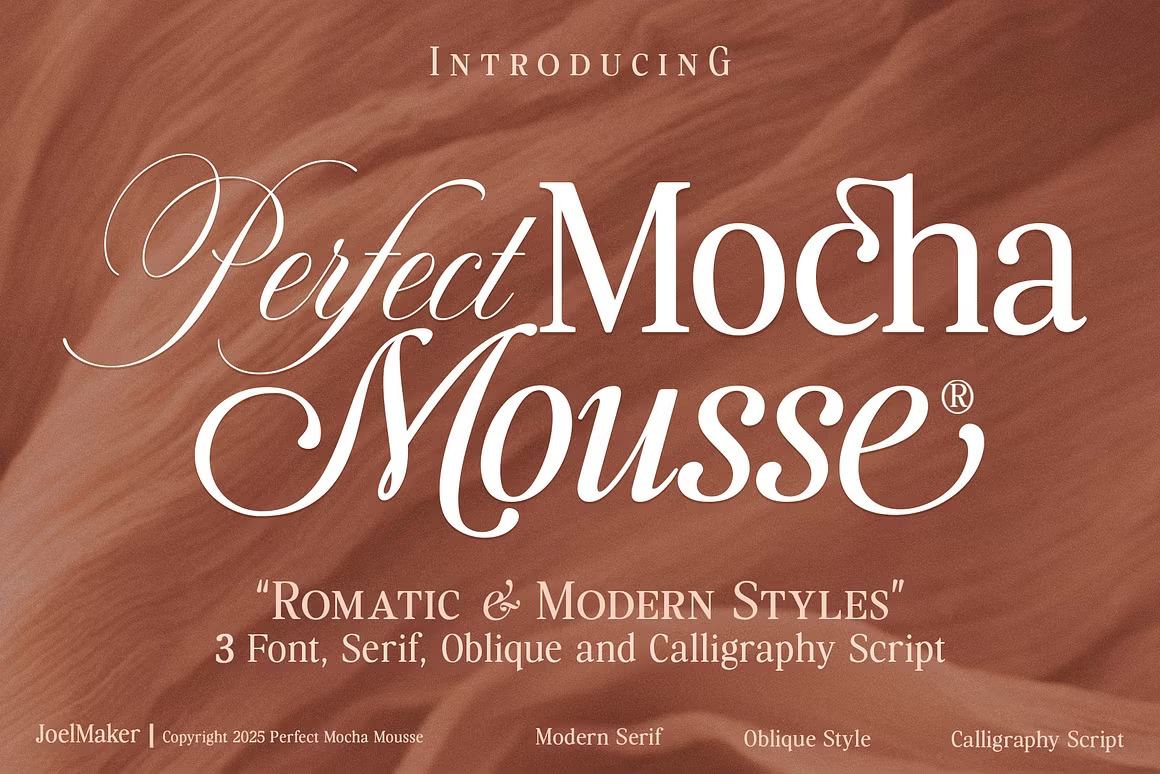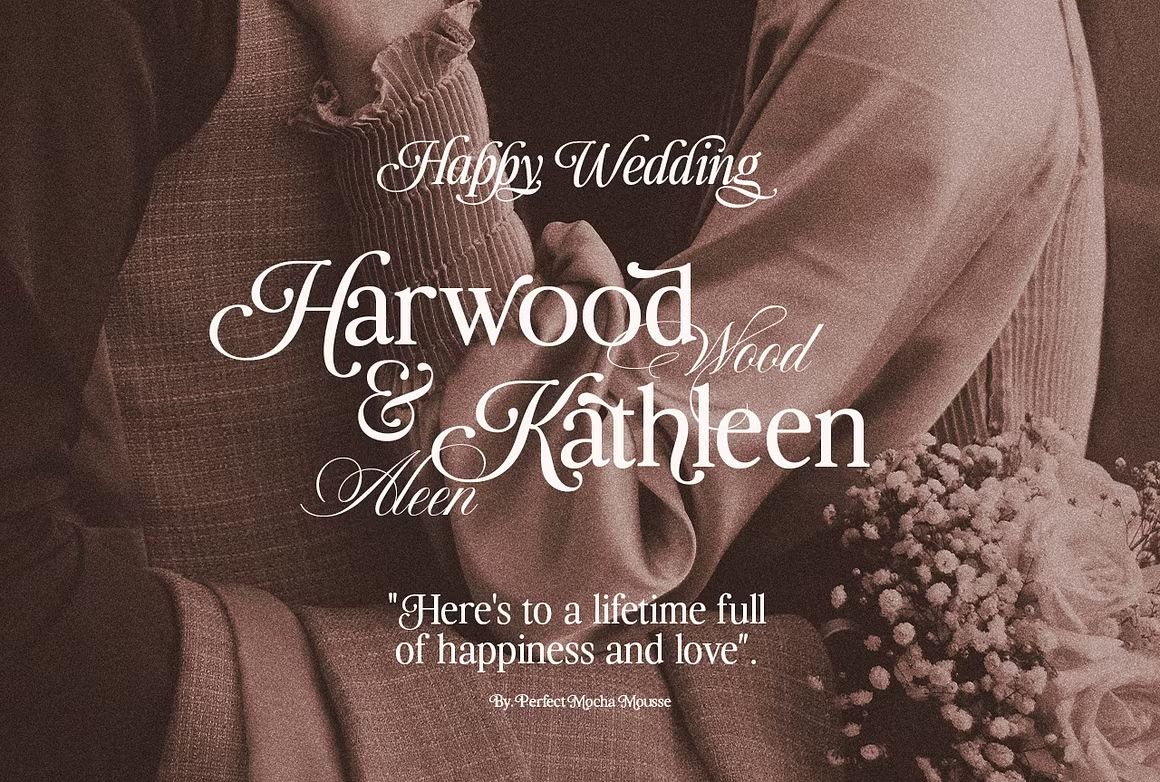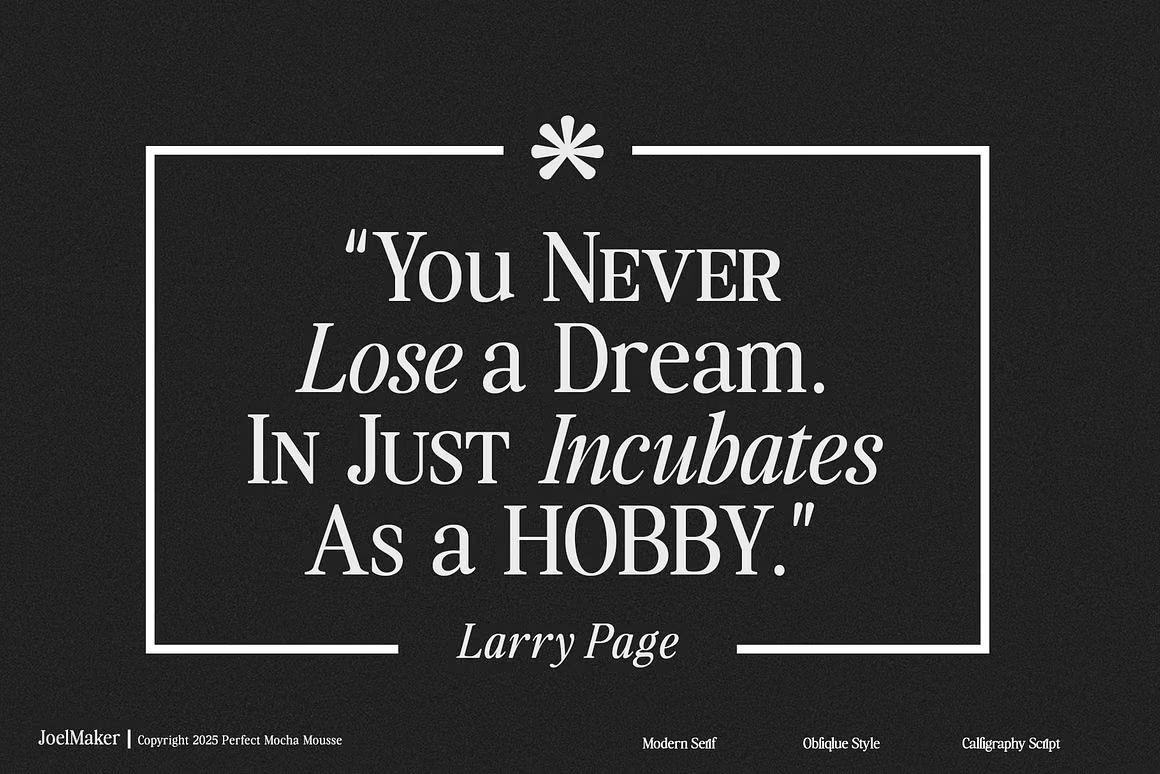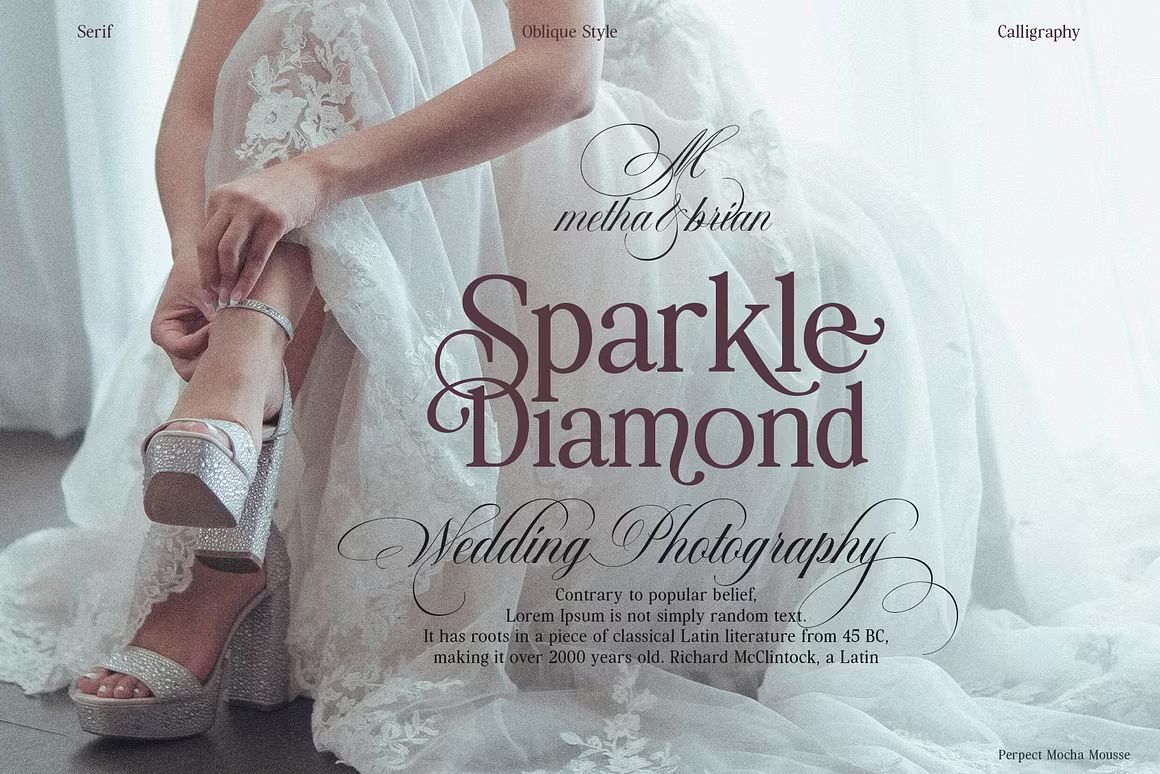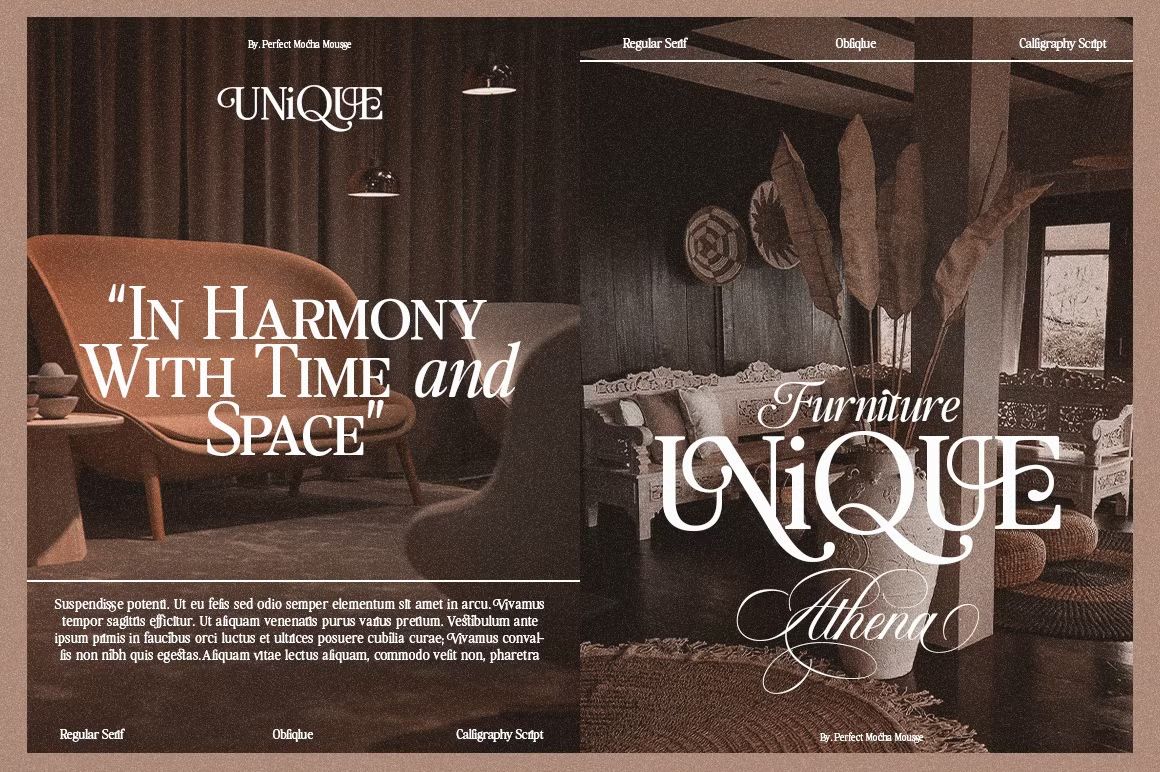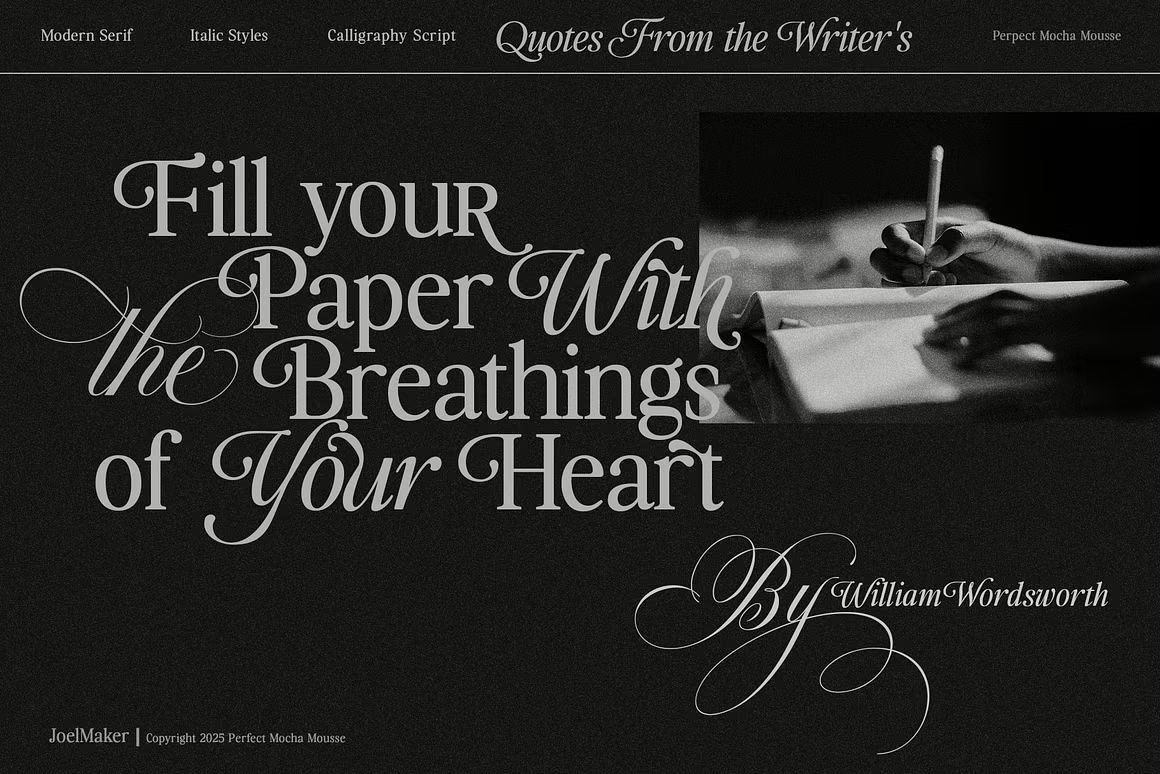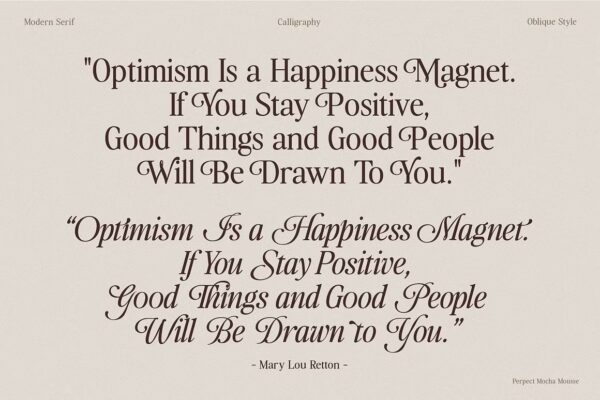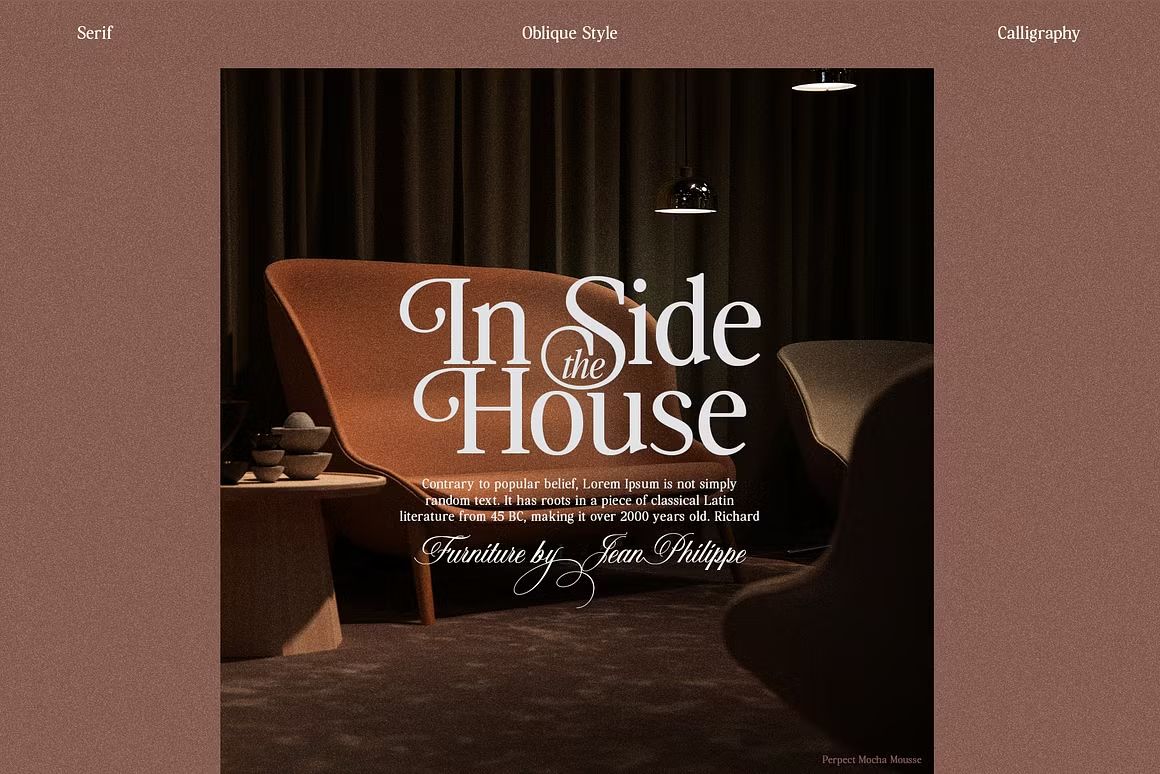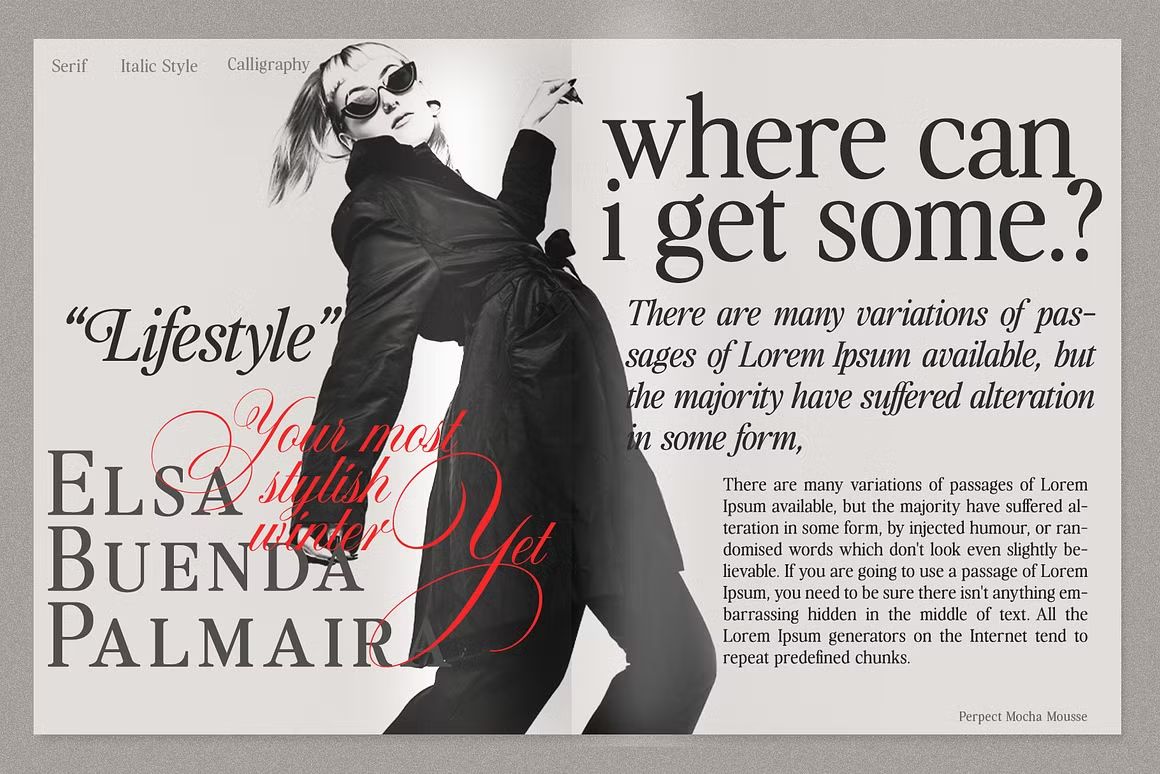
Perfect Mocha Mousse – Sans Serif Font
Perfect Mocha Mousse adalah font sans serif lembut dan elegan, cocok untuk branding, kemasan, dan desain kuliner. Format OTF/TTF/WOFF, siap digunakan.
Perfect Mocha Mousse adalah font sans serif modern dengan gaya lembut, elegan, dan mudah dibaca. Dirancang dengan proporsi yang seimbang dan ujung huruf membulat, font ini cocok untuk branding, kemasan produk, desain kuliner, logo, dan media sosial. Tampilan yang bersih dan manis menjadikan font ini sempurna untuk proyek desain yang mengutamakan kesan hangat dan profesional.
• Sans serif modern dengan ujung membulat dan lembut
• Ideal untuk branding, packaging, dan konten makanan
• Termasuk huruf besar, kecil, angka, dan simbol